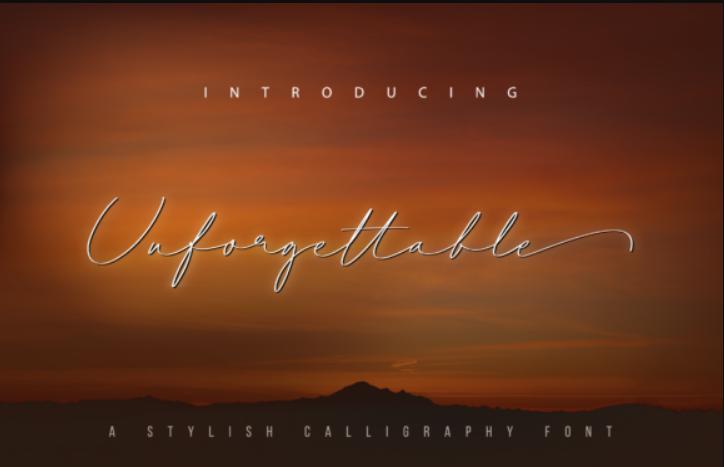
Unforgettable - это тонкий буквенный и изящный шрифт. Подпадайте под его восхитительный стиль и используйте его для создания великолепных дизайнов! Этот шрифт закодирован в кодировке PUA, что означает, что вы можете легко получить доступ ко всем глифам.